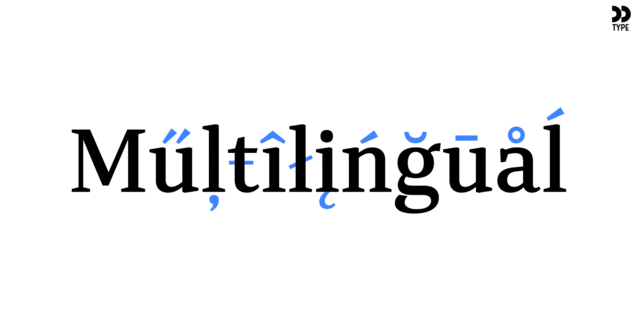
Rolleston Text – часть шрифтового семейства Rolleston. Его 14 начертаний созданы специально для текста в книгах, журналах или на сайтах.
Rolleston – строгое шрифтовое семейство с клиновидными засечками. Гарнитура содержит 42 начертания, по 14 для трех оптических размеров: Text, Title, и Display.
Эта гарнитура поддерживает десятки языков на латинице и кириллице, содержит различные опентайп-фичи, можество лигатур и большой набор альтернативных глифов. Это позволяет создавать уникальные заголовки и красивые сбалансированные тексты.
Шрифт разработал Олег Лищук в 2018 году.
убедительный, серьезный, строгий, спокойный, ровный, гармоничный, универсальный, понятный, деловой, уравновешенный, космополитичный, умеренный, техничный, современный, точный, логичный, практичный, оптимальный, доступный, статичный, культурный, образованный, устойчивый, умный, стабильный, твердый, солидный, качественный, городской